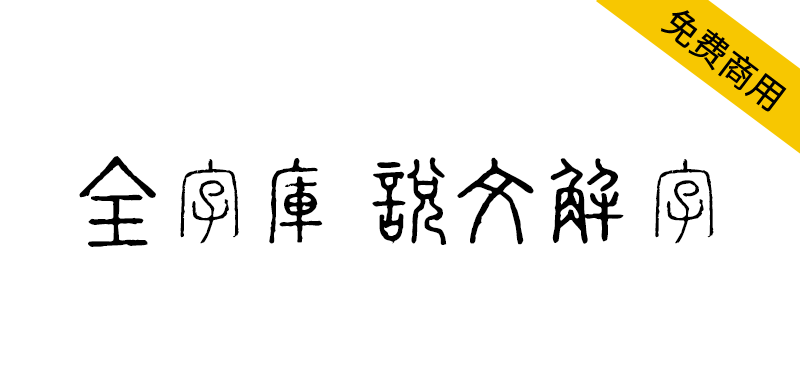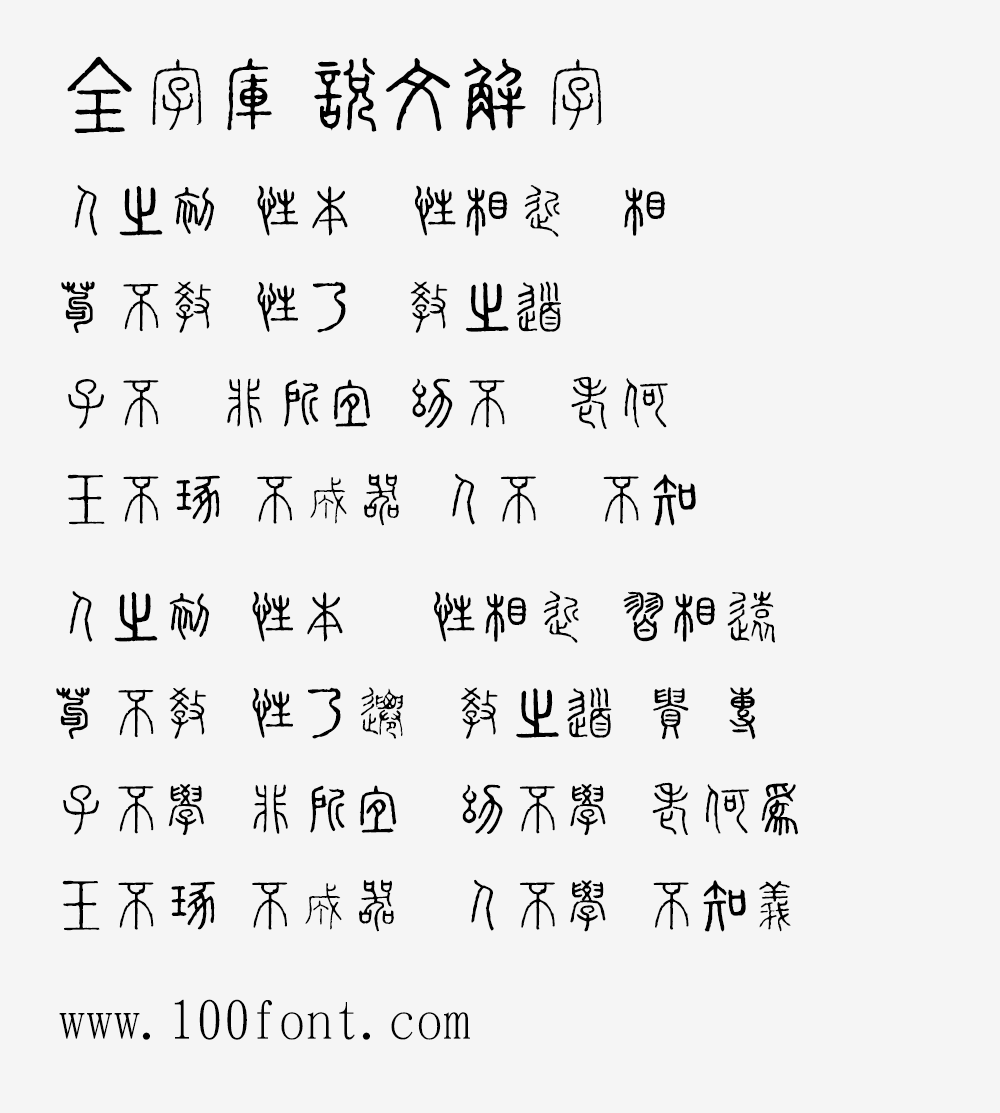
全字库说文解字是一款很特别的小篆风格中文字体,具有一种古色古香的历史韵味,以《中国台湾政府资料开放授权条款-第1版》的授权许可的方式发布。
《说文解字》是中国第一部系统地分析汉字字形和考究字源的字书,许慎著,成于安帝建光元年(121年)。原书十四篇,叙目一篇,正文以小篆为主,收9353字,又古文等异体同文1163字,解释十三万余字。
目前采用的版本为艺文印书馆所出版之《说文解字注》,后由南唐徐铉所校定,清代段王裁注之版本(世称大徐本)并参考黎明文化事业公司之《说文解字注》,及南唐徐铉所撰之《说文解字繁传》
由于说文解字原文与现行之Unicode编码并无一完整的对应,因此无法将所有的字形收录于本字体内,所以会有部分字码无法显示出正确的字形,使用的时候请多留意,目前收录于本字体内的字数共6721个字。